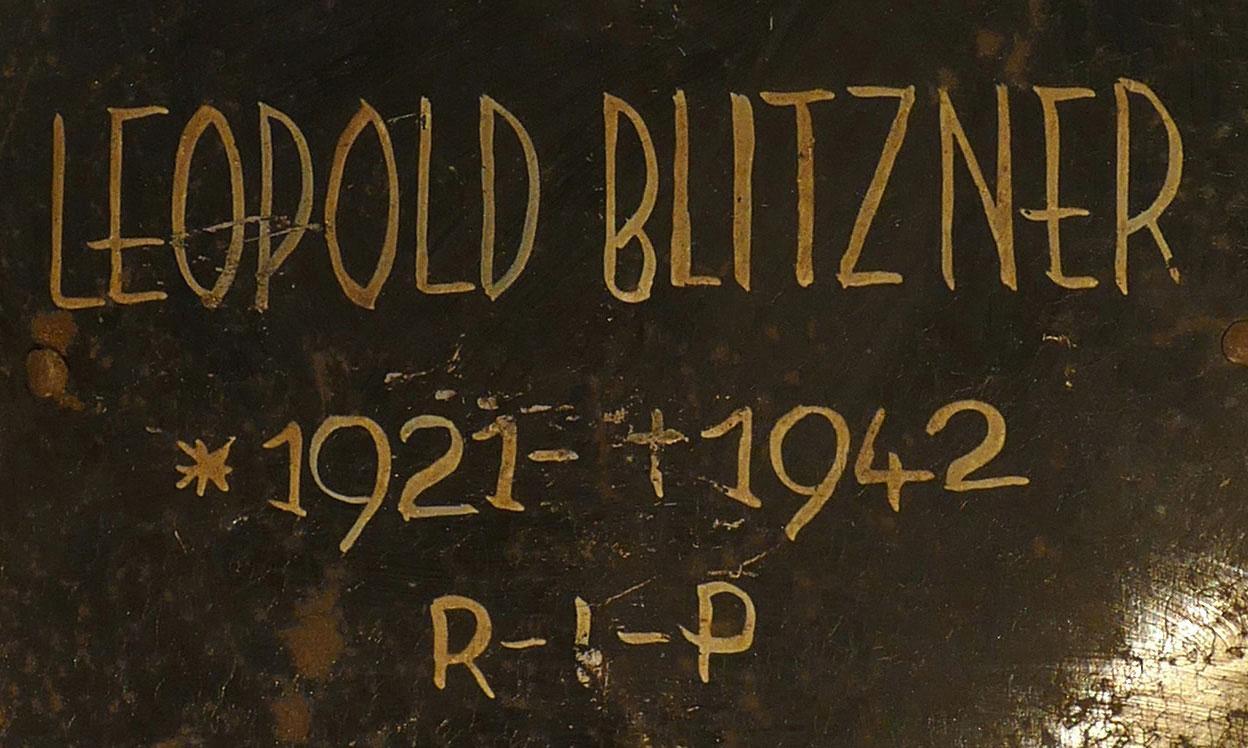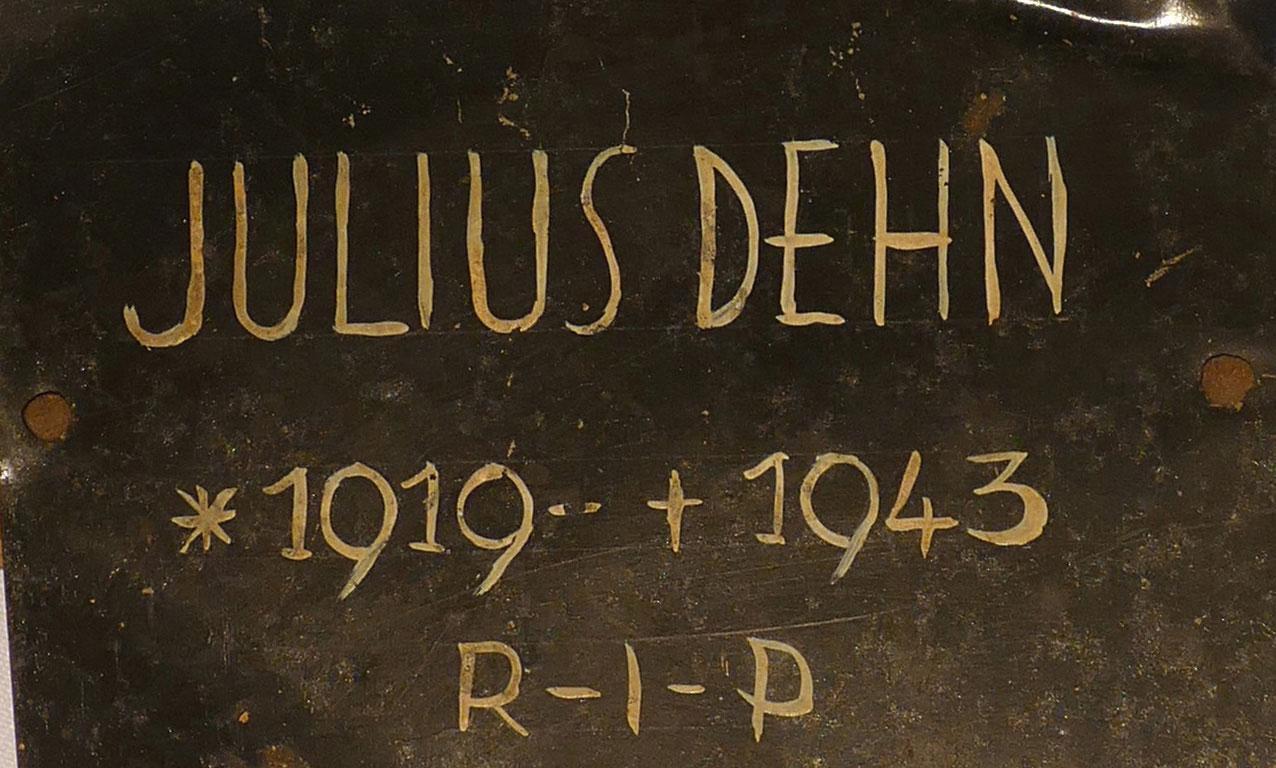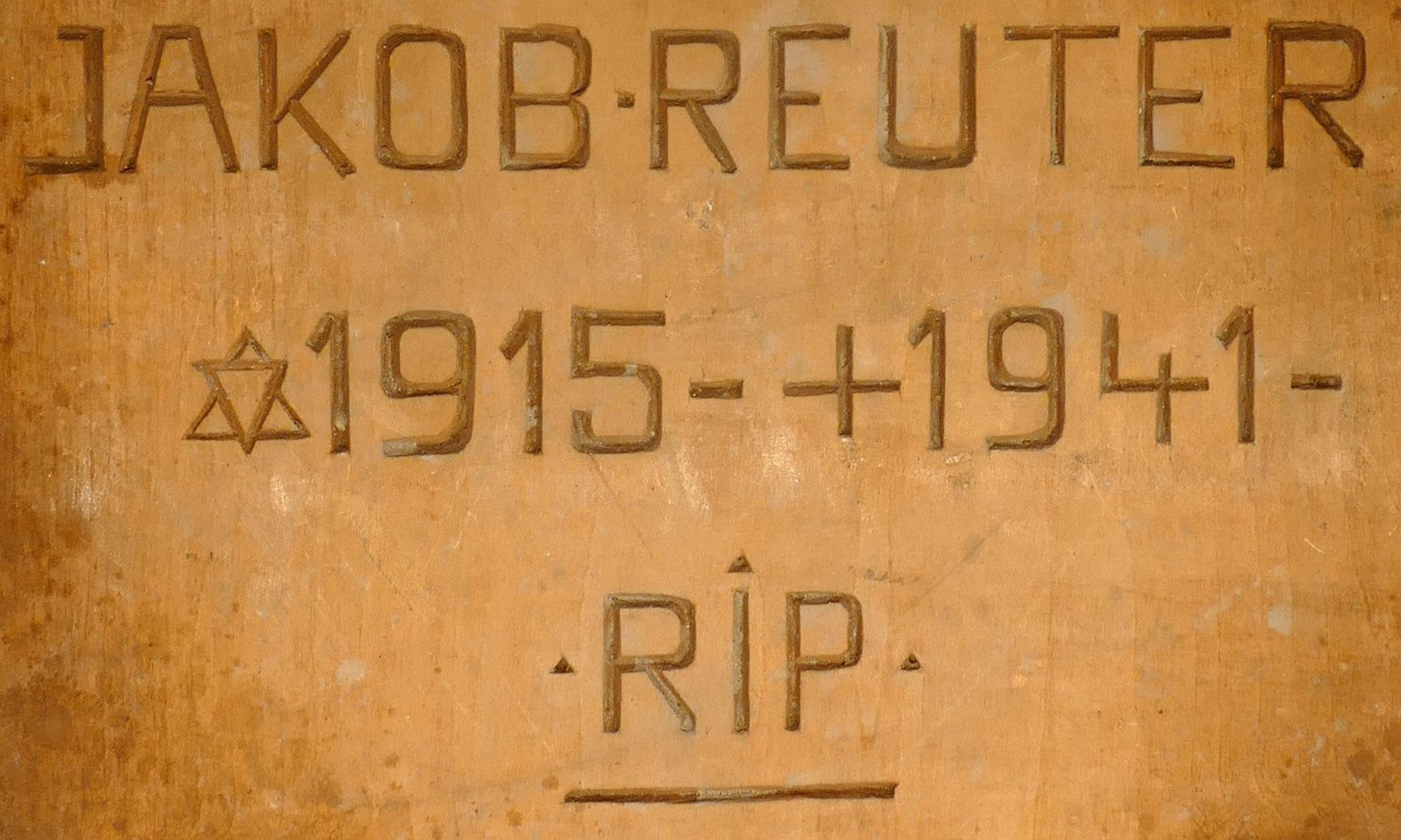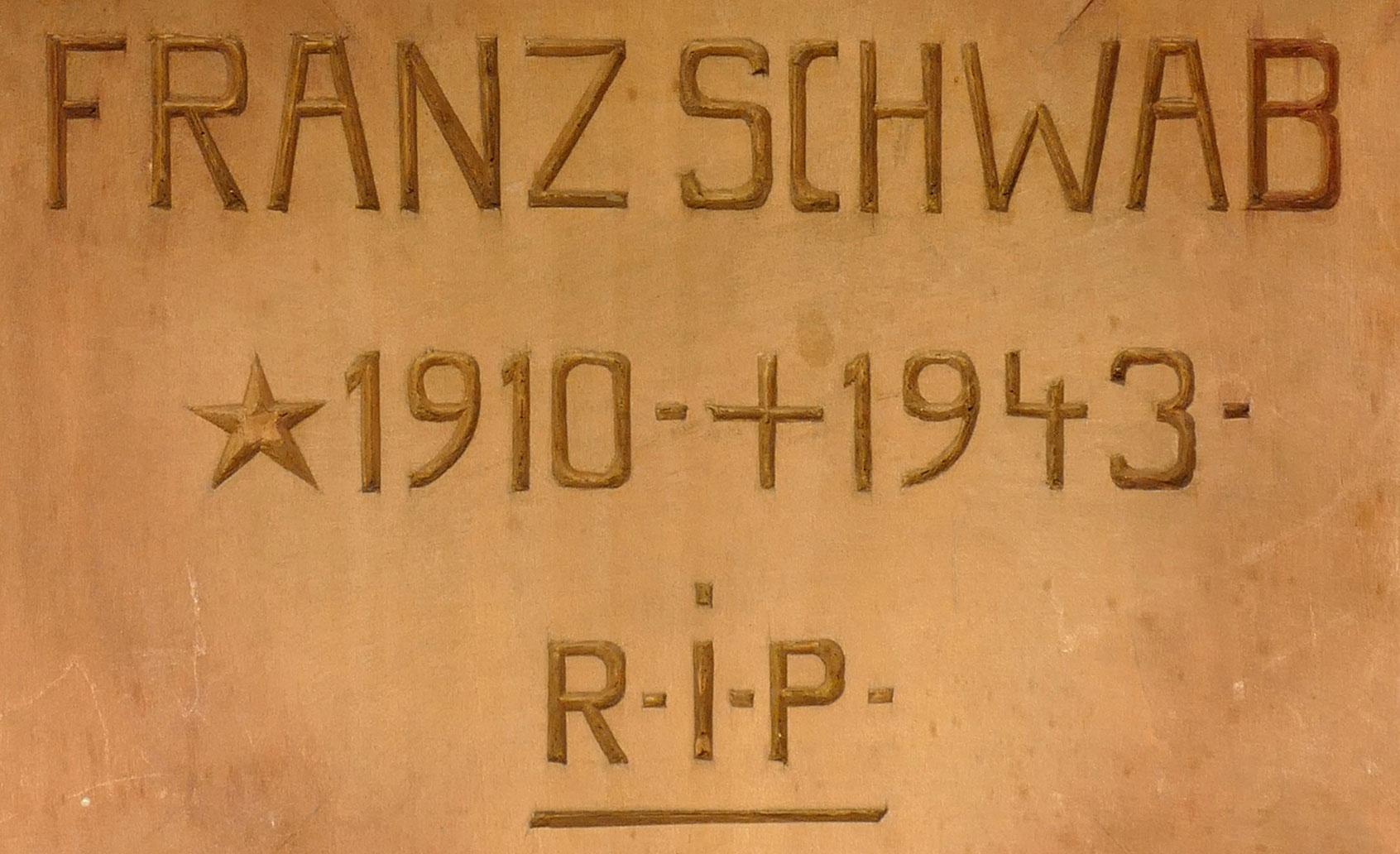
Bildhauerschrift aus den 1940ern
Der Bildhauer Heinrich Wohlfahrt verwendete bei Inschriften an seinen Werken beil. Typo. Was könnte ihm als Vorlage gedient haben? Welche Fonts gibt es, die dieser Schrift nahekommen?
Die handschriftlichen Beispiele (auf Metall gemalt) folgen einer anderen Ästhetik. Auch hier bin ich für Hinweise dankbar.